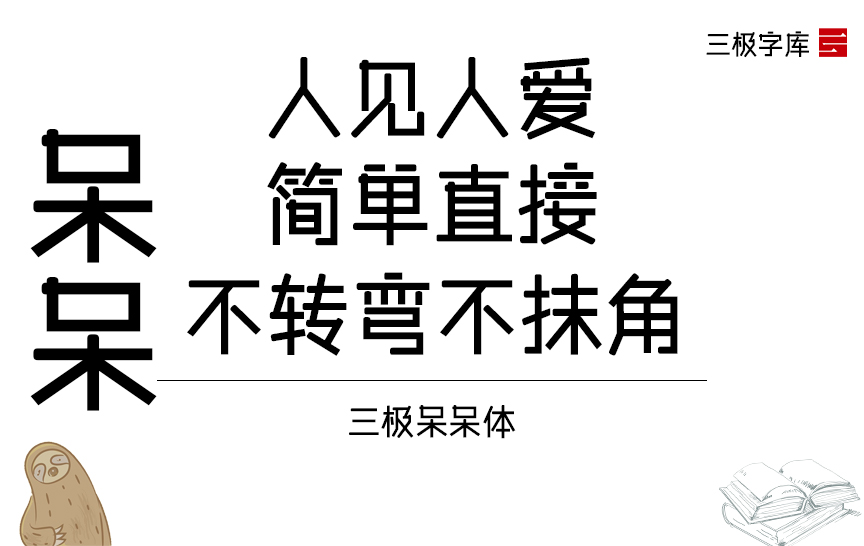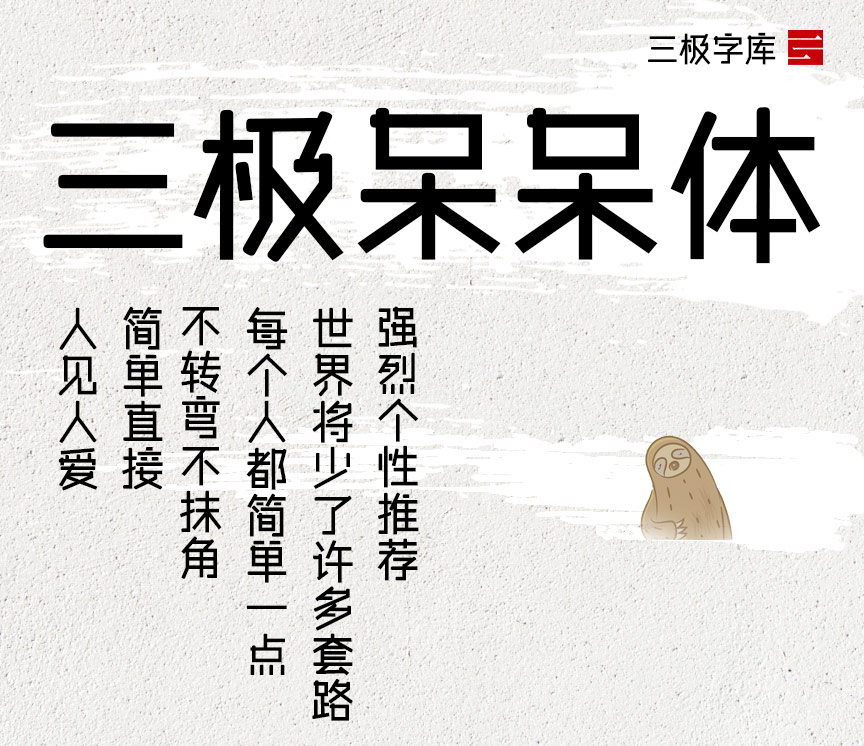
三极呆呆体是一款几何型构成的作品。整体风格率真,直接。字体稳重简洁,笔画平直、粗细匀称,起笔为圆头温柔可爱,收笔平直天真率气,又有强烈的个性。风格年轻、富有亲和力。它的灵感来源于管状物体,直接简单,坚韧不屈,给人一种直接干练的感觉。视觉效果简单易识别,实用性强。本作品适用于传统印刷媒介的标题、各类屏幕显示及影视字幕等。